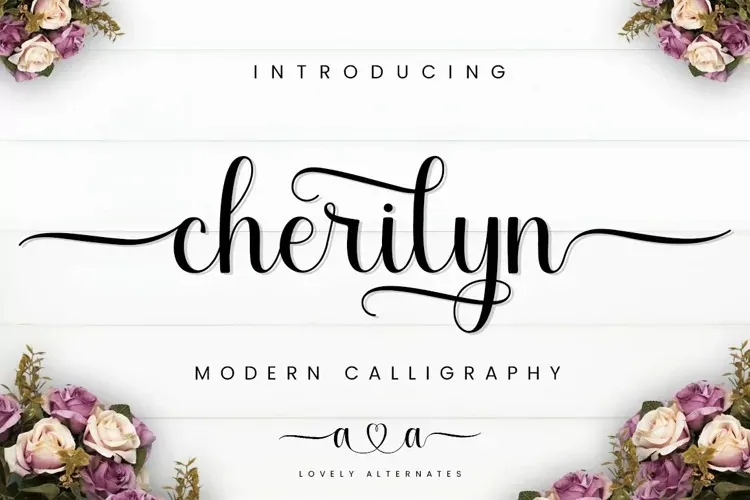
A Cherilyn Font é uma tipografia de script moderna com linhas alternativas na base que transmite sofisticação e elegância a qualquer projeto de design que você tenha em mente. Criada por Manjali Studio, esta fonte vai adicionar um toque luxuoso a seu trabalho, seja ele impresso ou digital. O grande destaque desta fonte é sua PUA encoding, o que lhe permite explorar todo o poder e riqueza de seus caracteres únicos e ligaturas sofisticadas com facilidade. Esta característica faz com que Cherilyn seja especialmente valiosa para designers e gráficos que procuram uma tipografia atemporal e moderna ao mesmo tempo. E não importa qual projeto você esteja trabalhando, a Cherilyn certamente se destacará.